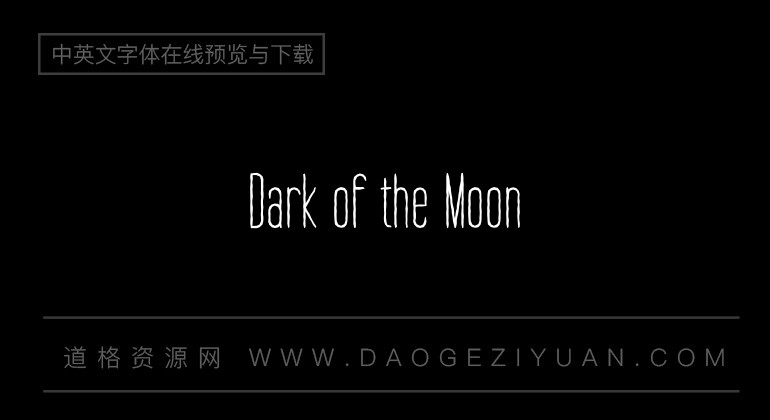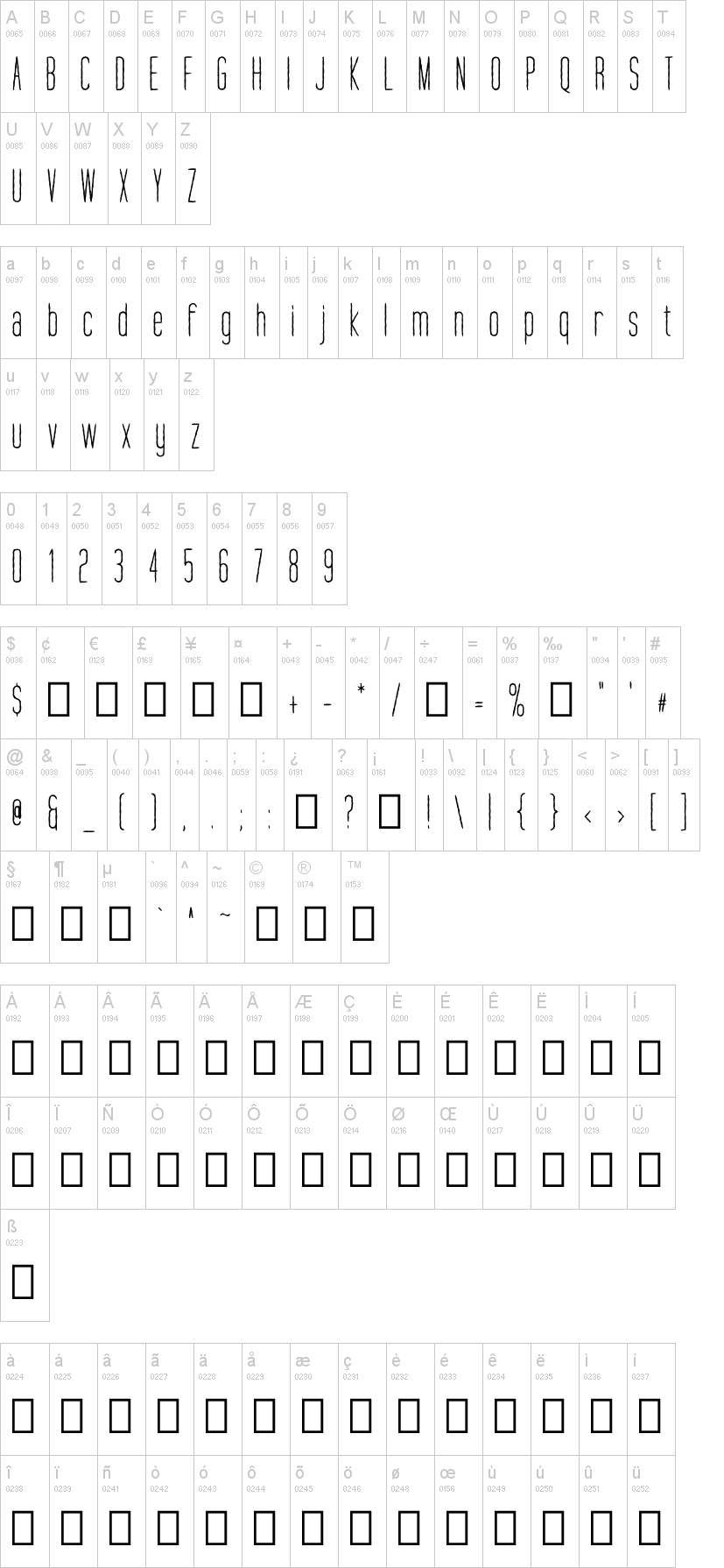
Dark of the Moon
暮色月亮体(Dark of the Moon)是一种免费的黑体字体,由Hendrick Rolandez于2013年设计。该字体的特点是有些字母有尖锐的角度和笔画,因此看起来有些锋利和现代感。暮色月亮体适用于标题、海报、标志、包装设计等,可用于商业和个人项目。该字体包括所有基本拉丁字母和数字,以及符号和标点符号。
Dark of the Moon是一款非常不错的手写艺术字体,具有很好的视觉感,适合于文化类的宣传设计、商业类品牌的广告和产品包装设计以及个性化文字排版等较多场景。
Dark of the Moon字符映射图